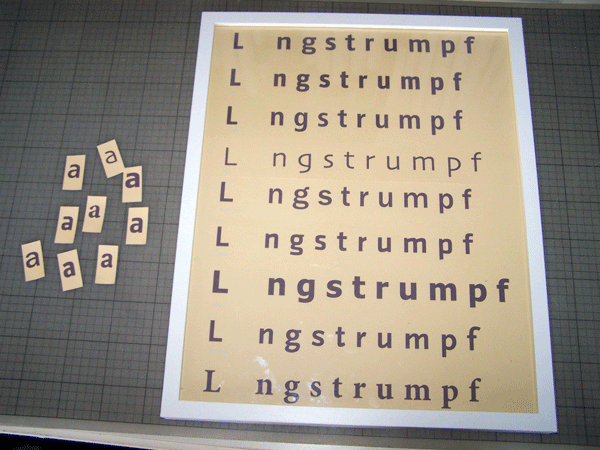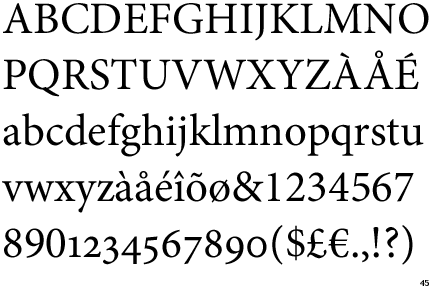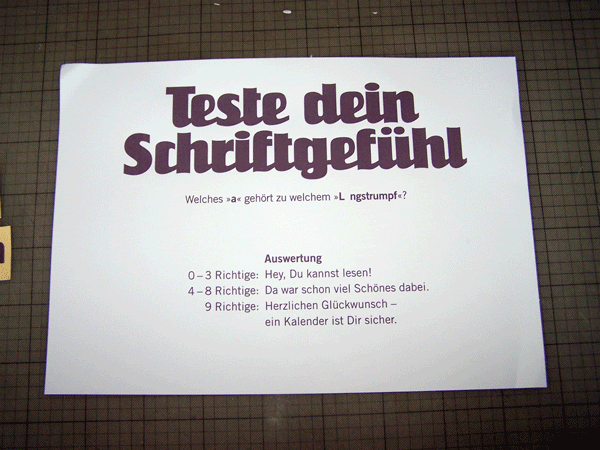
ein großer Spaß war der Test zum Schriftgefühl. Als Hauptpreis gab es den typografischen Kalender, als Trostpreis ein Toffifee. Etwa 120 Leute testeten ihr Schriftgefühl, 16 Kalender wurden gewonnen, allen voran Kathrin mit bravurösen 14 Jahren und dem gleichzeitigen Geschwindigkeitsrekord. Sie überlegt gerade, ob sie ein Praktikum machen möchte :-)
Zur allgemeinen Belustigung habe ich das Quiz kurz vor dem Aufräumen hier reingestellt, auch auf die Gefahr hin, breite Langeweile durch Unterforderung hervorzurufen.
Coole Sache! Mit sowas kriegt man doch auch Noch-Nicht-Type-Aficionados dazu, sich über sowas Gedanken zu machen… fein.
Und: Sagst Du mir bitte, wie die Schrift bei «Teste dein Schriftgefühl» heißt? Tausendmal gesehn, tausendmal den Namen nicht gewusst … :?
Es gibt auch eine Low-Budget-Variante von Nick Curtis.
danke für die blumen, ist super angekommen. Gerade Leute, die nichts mit Typo zu tun haben, waren sehr erfolgreich und haben genau hingeschaut. Einige Grafiker waren da zu selbstsicher und hatten - hüstel - nicht gerade wenig fehler...
Welche Schriften sind es denn?
Es gibt einen Kalender zu gewinnen :-)
Welche Schriften sind es denn? Es gibt einen Kalender zu gewinnen :-)
Ui, nicht einfach, nein, nicht einfach. Zumindest für mich.
Skia ist noch die markanteste darunter. Dann meine ich Signa, News Gothic, Myriad, Scala Sans und möglicherweise Franklin Gothic zu erkennen.
schon mal drei Richtige :-)
Also, dann tu ich auch mal. Ich dachte, mit so wenigen Tipps brauch ich mich gar nicht erst melden … :?
Ich sehe da Skia (4), Franklin Gothic (5), Verdana Bold (dritte von unten), eventuell irgend einen Frutiger-Schnitt (3), oder ist das etwa Myriad? Ich meine da eher Frutiger zu erkennen. News Gothic seh ich nirgends.
Die Antiqua macht mich fast wahnsinnig, hab gestern meine gesamte Fontsammlung durchgeschaut, aber dieses t find ich nirgends, vor allem nicht in Verbindung mit diesem g. :?
1. ??
2. ??
3. Frutiger Condensed
4. Skia
5. Franklin Gothic
6. ??
7. Verdana bold
8. Scala Sans
9. ??
wer will lösen?
Die Antiqua hat mich ja sofort an die »Leitura News« erinnert, da stimmt aber m.E. die Tropfenform vom r und f nicht und das t ist auch nur so ähnlich ... :? :? :?
Vielleicht ist es auch viel einfacher und es ist die Minion?